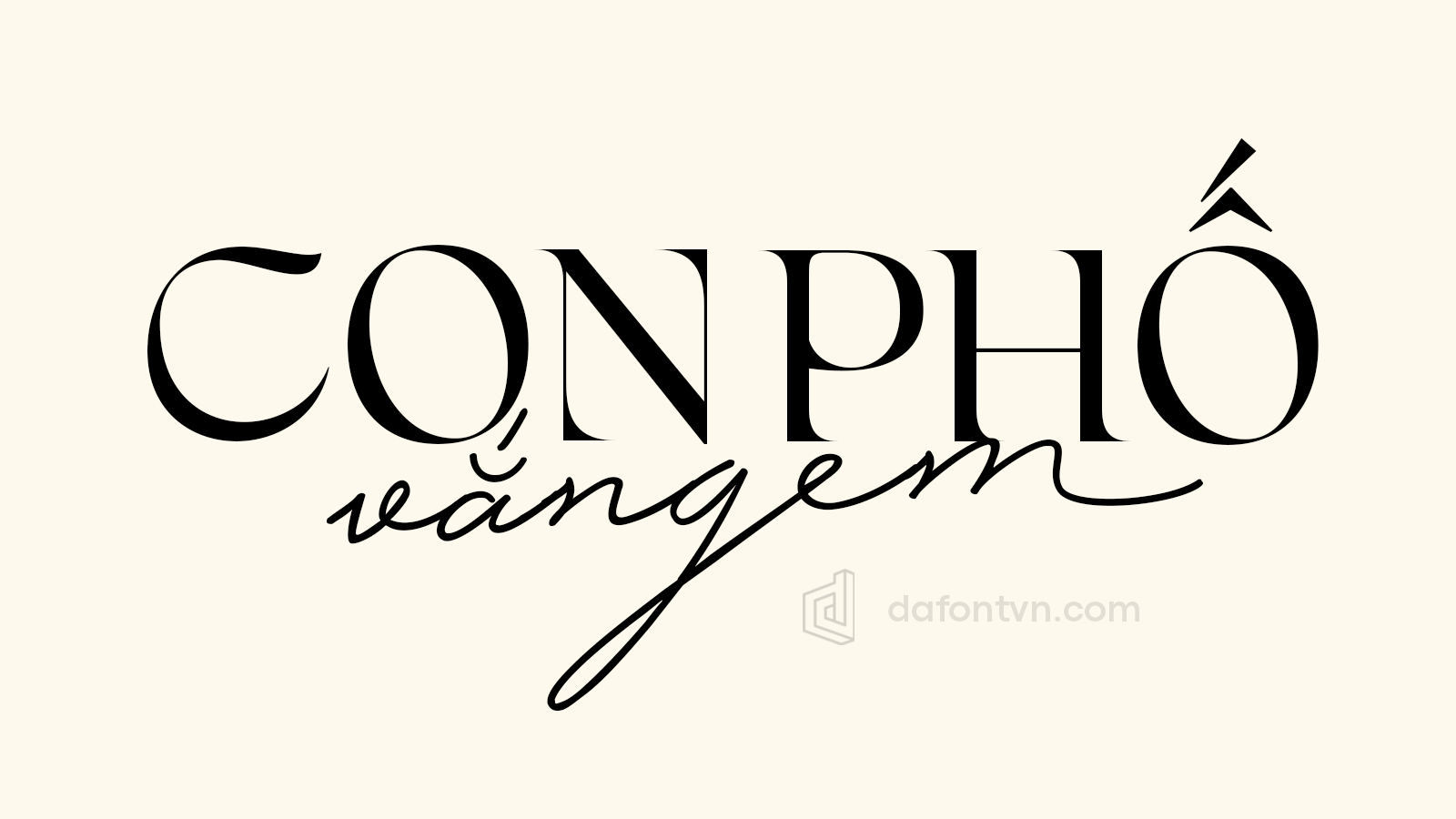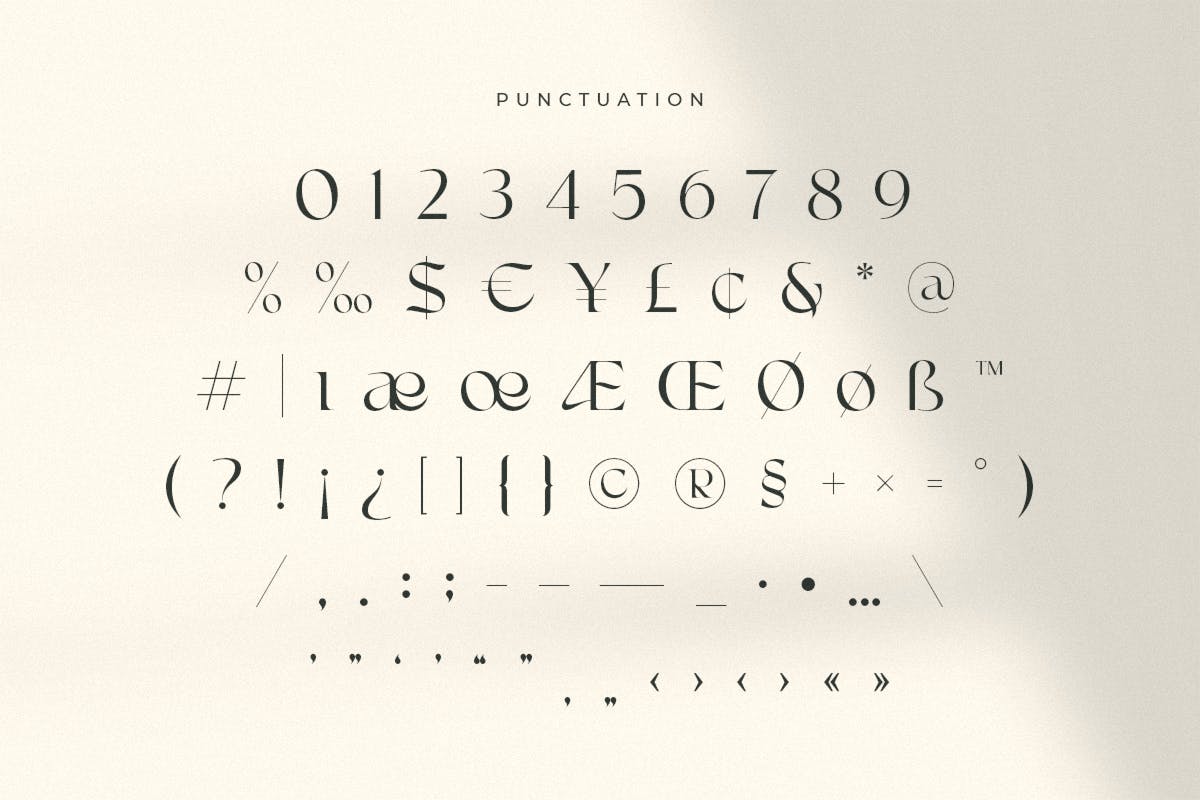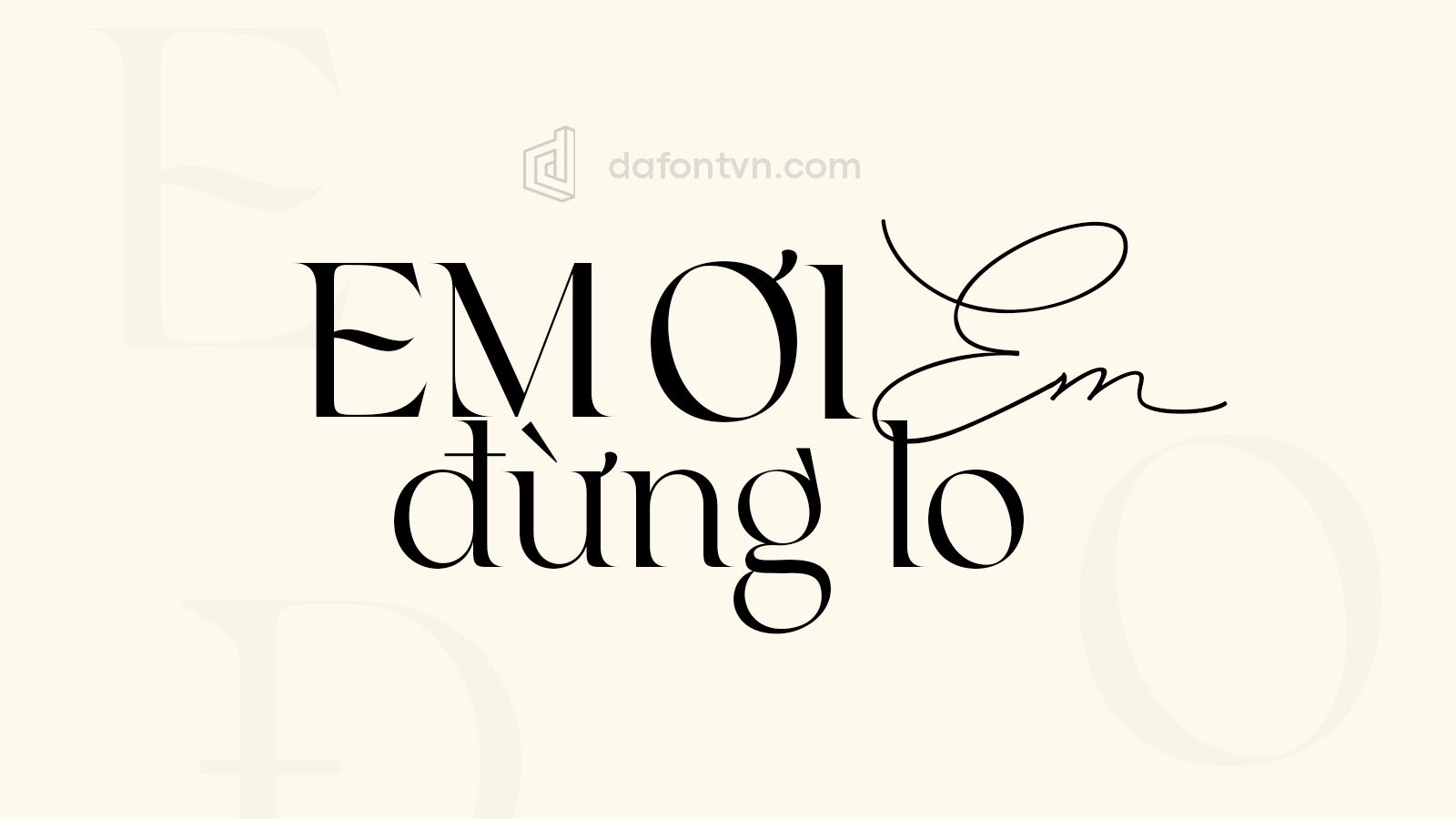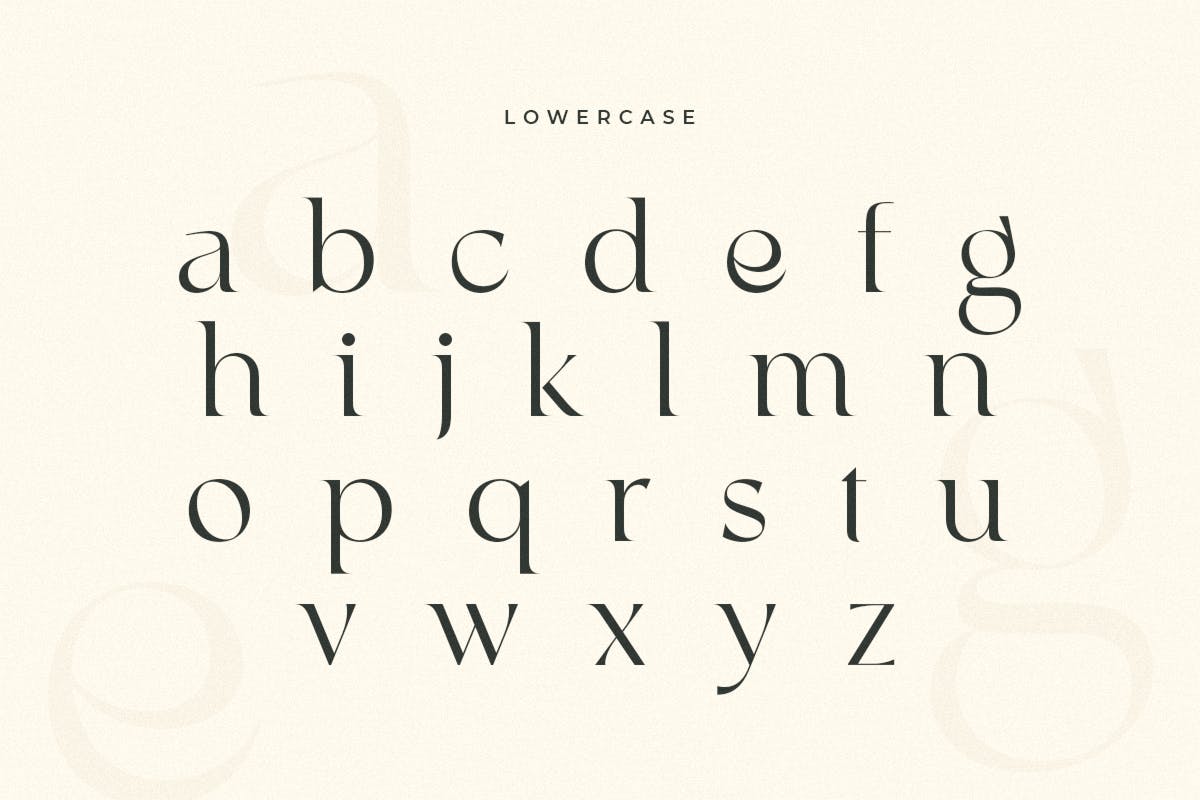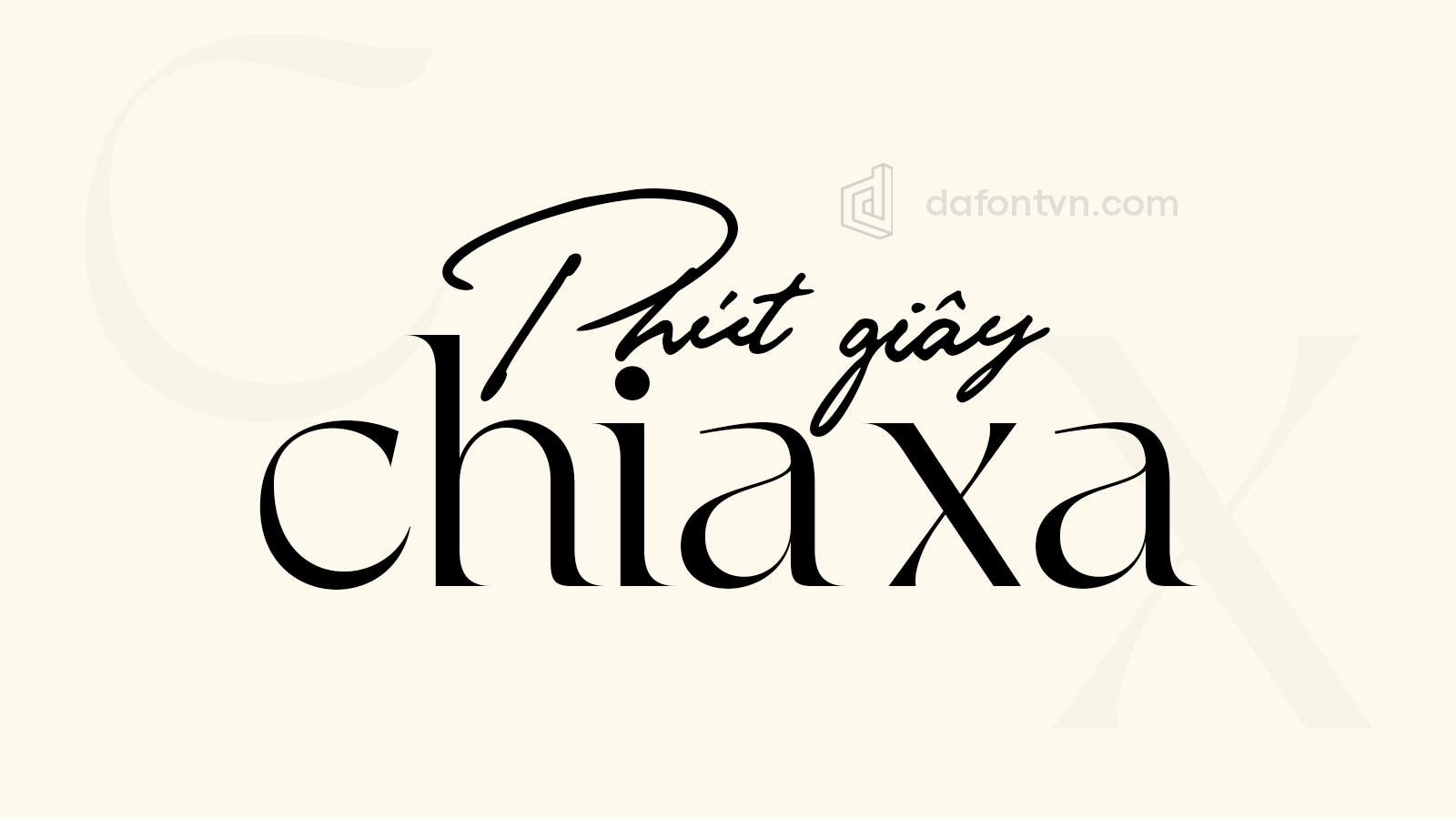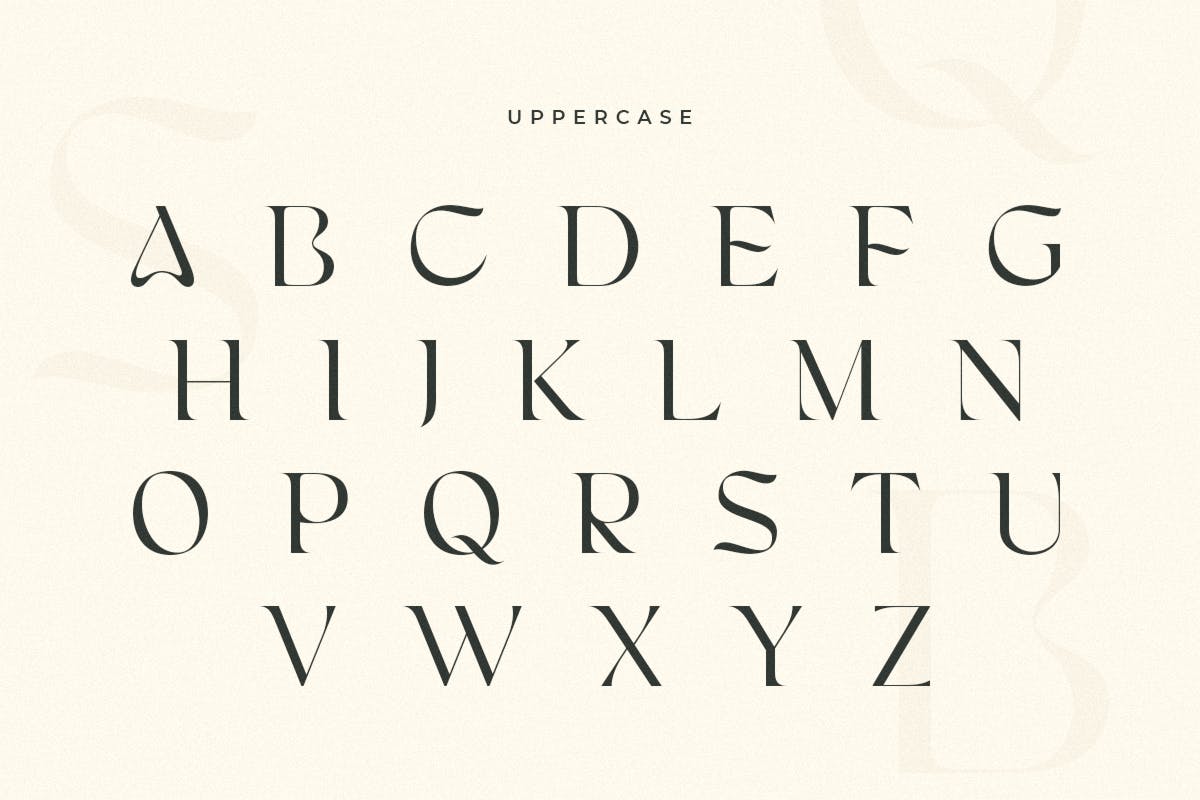
[Serif] Font Big Bang Việt Hóa cực đẹp
Font Big Bang Việt Hóa mang đến một vẻ đẹp hấp dẫn với các nét chữ được thiết kế hiện đại phù hợp cho hầu hết các thiết kế của bạn. Các nét chữ được tác giả thiết kế khá tỉ mỉ phù hợp cho các thiết kế logo, thương hiệu, typo, thời trang, mỹ phẩm…
Font được Việt hóa, kerning và features đầy đủ.